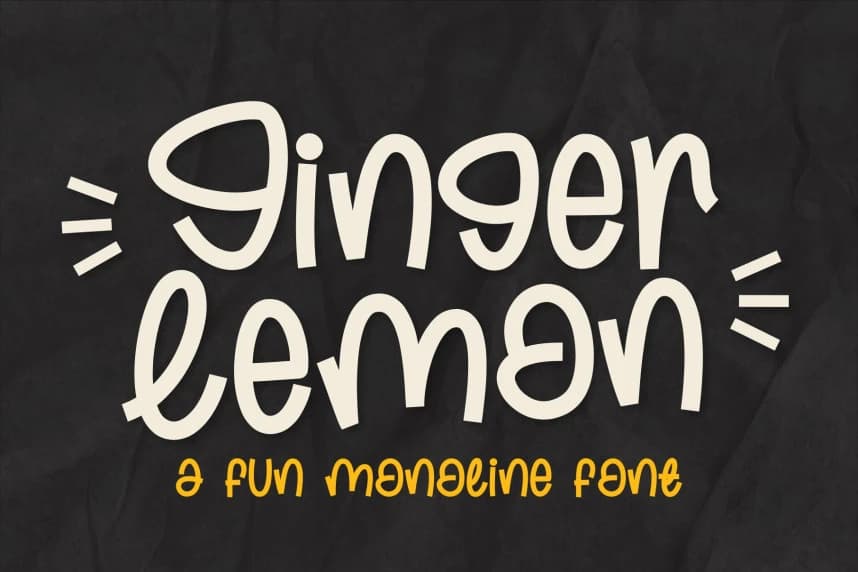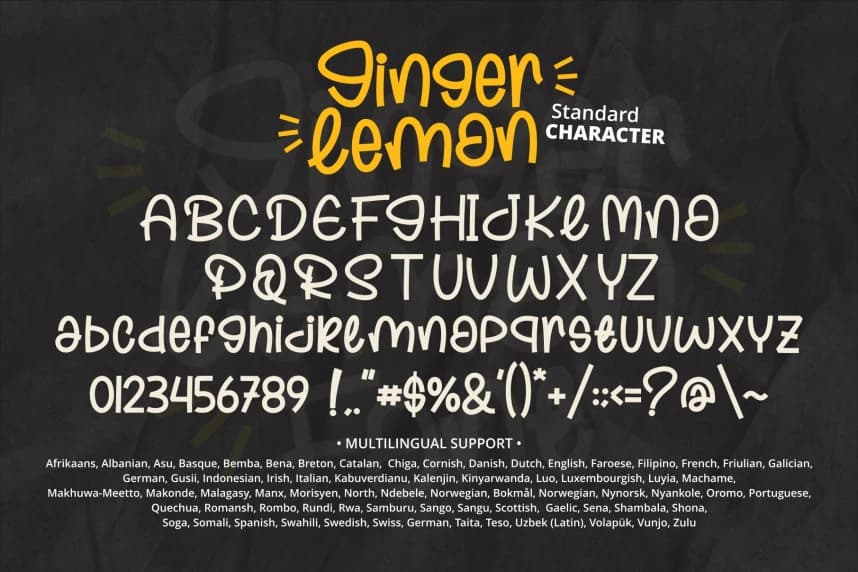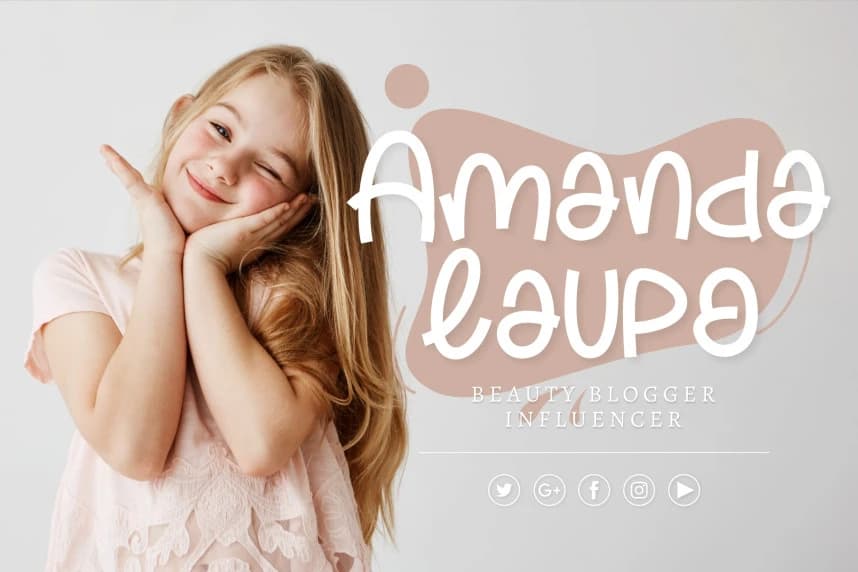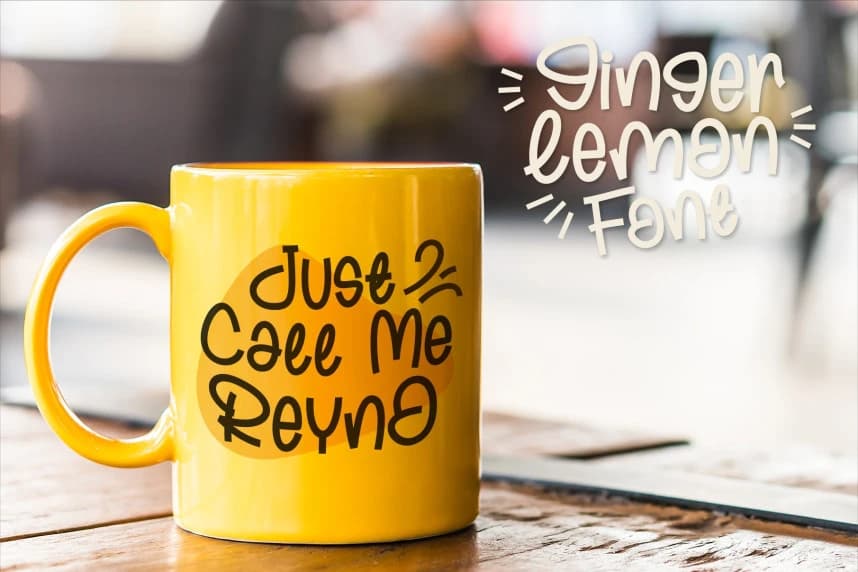
Ginger Lemon Font
Ginger Lemon Font, çocuk tasarımları için mükemmel, neşeli ve oyuncu kalın monoline bir yazı tipidir! Bu yazı tipi, eğlence ve hayal gücü hissi yaratan cesur ve tekdüze çizgilere sahiptir. Akıcı eğrileri ve dostça hatlarıyla afişler ve hikaye kitapları için idealdir.
Ginger Lemon Font, çocuk tasarımları için mükemmel olan neşeli ve oyunbaz bir kalın monoline fontudur! Bu yazı tipi, eğlence ve oyun hissi veren kalın, düzgün çizgilere sahiptir. Akıcı kıvrımları ve dostane şekilleri, afişler ve öykü kitapları için idealdir.